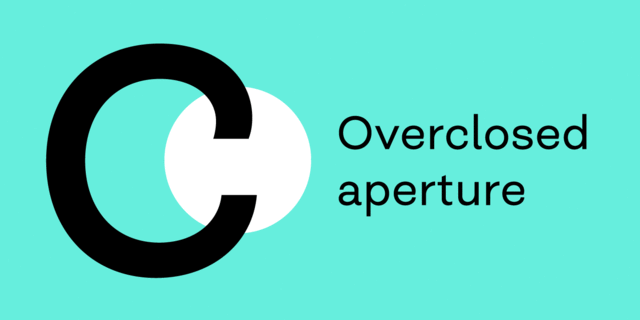
Більш компактна версія шрифту Closer. Його можна охарактеризувати як швейцарський гротеск з закритою апертурою. Шрифт має гуманістичні форми, він виглядає менш прісним, але все ще відносно нейтральним.
Closer складається з 9 накреслень (в цілому 18 стилів), має розширену підтримку мов, включно з кирилицею, і володіє широкими можливостями з 7 стилістичними наборами для змішування і знаходження найкращих поєднань.
Шрифт розробив Андрій Константинов у 2019 році.